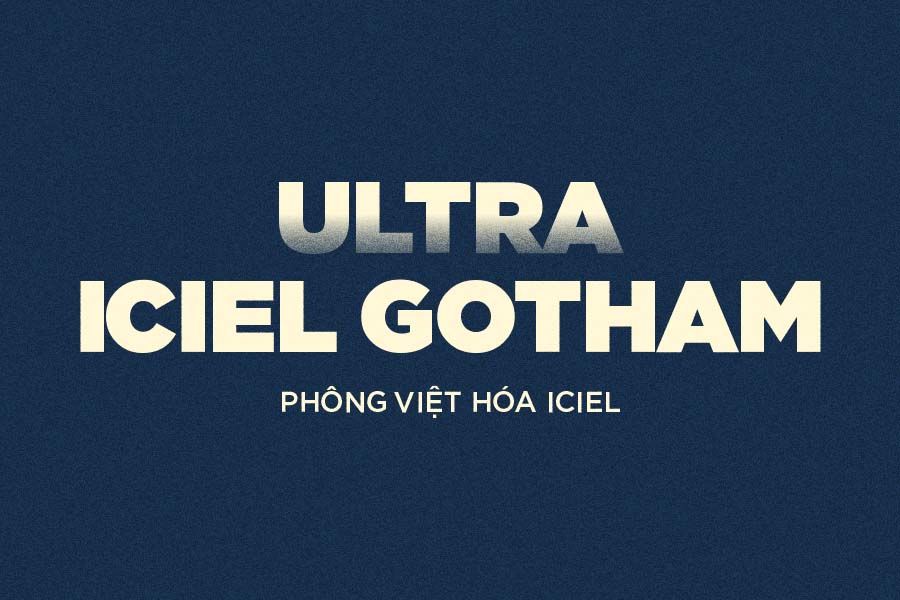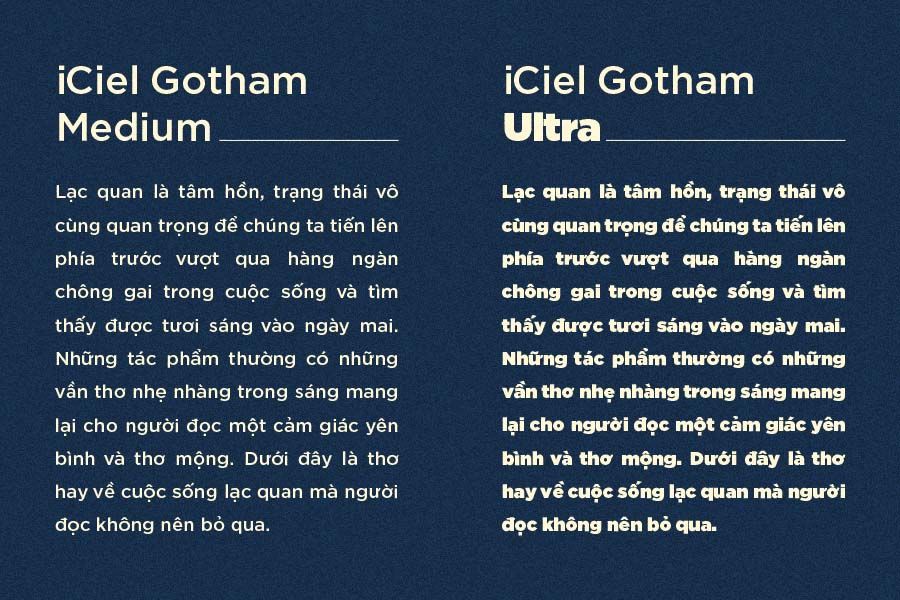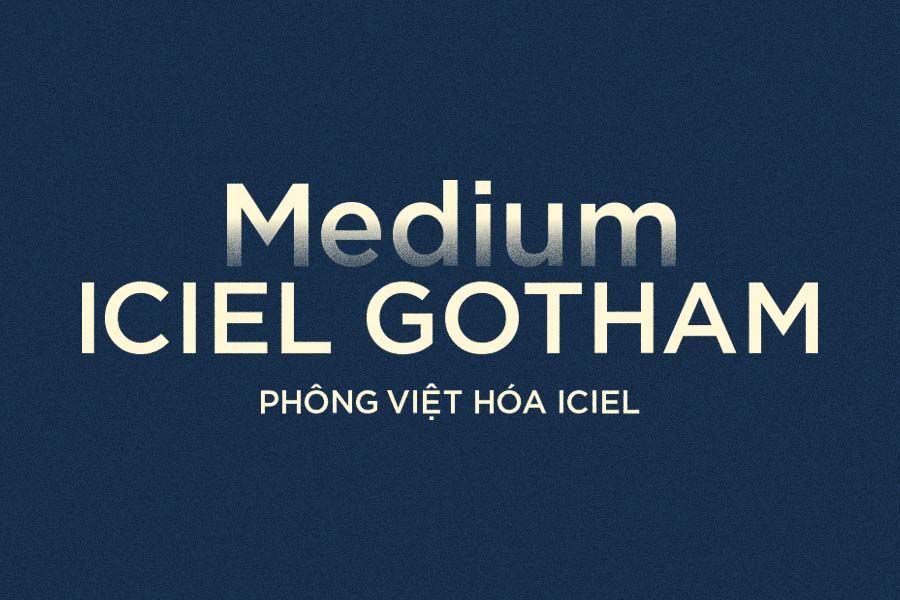
Trong thế giới thiết kế, Gotham là một trong những font sans-serif nổi tiếng nhất. Được thiết kế bởi tác giả Tobias Frere-Jones vào năm 2000 và phát hành bởi Hoefler & Co., Gotham nhanh chóng tạo nên dấu ấn nhờ thiết kế hình học chuẩn mực, cân đối và cực kỳ dễ đọc. Font này từng được ứng dụng trong nhiều chiến dịch truyền thông lớn, nổi bật nhất là chiến dịch tranh cử của Barack Obama năm 2008, khiến Gotham trở thành biểu tượng cho sự hiện đại, gần gũi và minh bạch.
Phiên bản iCiel Gotham Việt hóa
Nhóm iCiel đã Việt hóa bộ font Gotham, giúp font hỗ trợ đầy đủ dấu tiếng Việt. Khác với bản gốc có hơn 60 trọng lượng, phiên bản iCiel tinh gọn chỉ giữ lại 2 kiểu chữ tiêu biểu:
• iCiel Gotham – Medium
• iCiel Gotham – Ultra
Sự tinh giản này giúp designer Việt dễ dàng chọn lựa, vừa đáp ứng nhu cầu cơ bản, vừa duy trì được phong cách đặc trưng của Gotham.
iCiel Gotham – Medium: Cân bằng và hiện đại
• Nét chữ dày vừa phải, hình học rõ ràng, dễ đọc.
• Phù hợp cho tiêu đề phụ, văn bản, brochure hoặc website.
• Mang đến cảm giác chuyên nghiệp, gọn gàng và hiện đại.
iCiel Gotham – Ultra: Mạnh mẽ và nổi bật
• Đường nét cực dày, in đậm, gây ấn tượng mạnh.
• Lý tưởng cho poster, banner, logo hoặc thiết kế cần nhấn mạnh.
• Tạo cảm giác chắc chắn, uy tín và thu hút thị giác ngay lập tức.
Vì sao nên chọn iCiel Gotham Việt hóa?
1. Hỗ trợ đầy đủ tiếng Việt: Không lo lỗi dấu.
2. Tính ứng dụng cao: Medium cân bằng, Ultra mạnh mẽ.
3. Thương hiệu toàn cầu: Gotham vốn là font chữ kinh điển, được ứng dụng rộng rãi.
4. Thiết kế hiện đại: Phù hợp với xu hướng tối giản, tinh gọn.
Ứng dụng thực tế
• Logo & thương hiệu: Tạo sự chuyên nghiệp và tin cậy.
• Truyền thông & quảng cáo: Nổi bật, thu hút ánh nhìn.
• Ấn phẩm in ấn: Rõ nét ở nhiều kích thước.
• Thiết kế số & website: Tối ưu trải nghiệm đọc.
2. Khác biệt giữa iCiel Gotham và SVN Gotham là gì?
→ iCiel chỉ có 2 kiểu (Medium, Ultra), còn SVN Gotham đa dạng hơn về trọng lượng.
3. Font Gotham phù hợp nhất cho thiết kế nào?
→ Phù hợp với logo, thương hiệu, poster sự kiện, tạp chí, và website hiện đại.